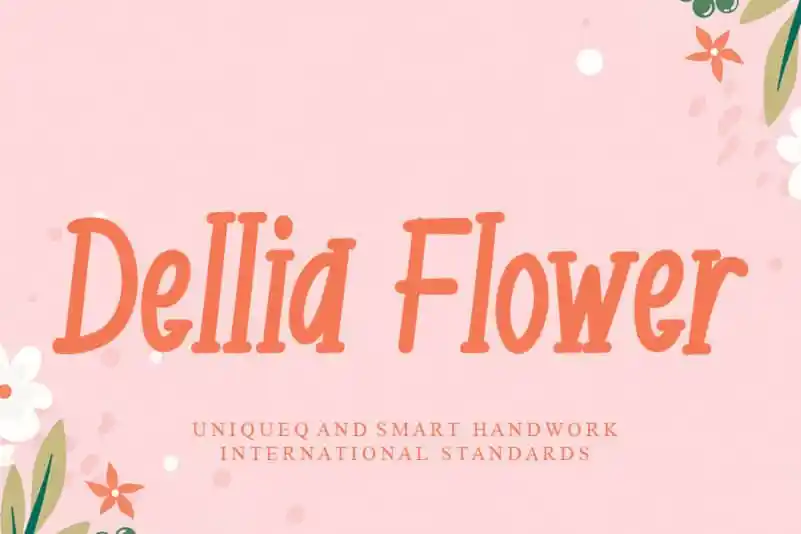
Dellia Flower Display Font – Download Grátis
A fonte Dellia Flower Display é uma escolha perfeita para quem busca um toque autêntico e casual no design dos seus projetos digitais. Idealmente, ela foi criada para aqueles momentos quando você quer adicionar um ar pessoal a seu trabalho sem comprometer a elegância. Com sua característica de desenho à mão livre, o Dellia Flower Display carrega um charme elegante que se destaca em qualquer projeto. Seu estilo distintivo e eterno é uma opção perfeita para aqueles momentos quando você deseja inovar sem comprometer a versatilidade da fonte. Este é o ideal para quem busca uma fonte de desenho à mão livre que vai além do básico, oferecendo um toque autêntico e original que pode tornar seu design ainda mais único e especial. Sem dúvida, Dellia Flower Display se destaca como a escolha perfeita para aqueles projetos digitais especiais.